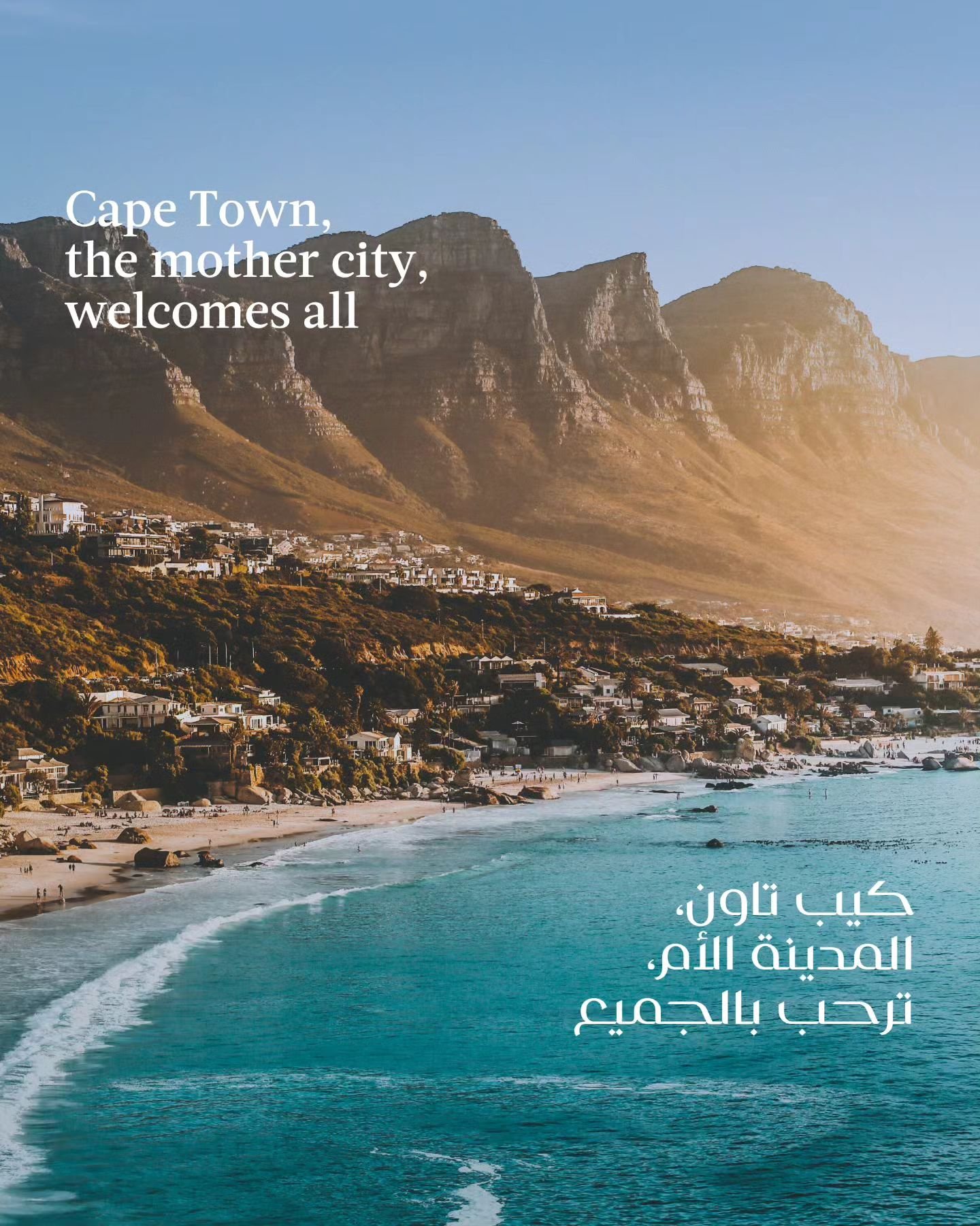
استخدام خط ايوان ظاظا – LIST Magazine
ايوان ظاظا هو خط عربي حديث عالي التباين صممه احمد ظاظا . التصميم مستوحي من اسلوب الخط الكوفي و متاثر باسلوب النسخ. يوازن ايوان ظاظا بين الاذواق الكلاسيكية و المعاصرة.